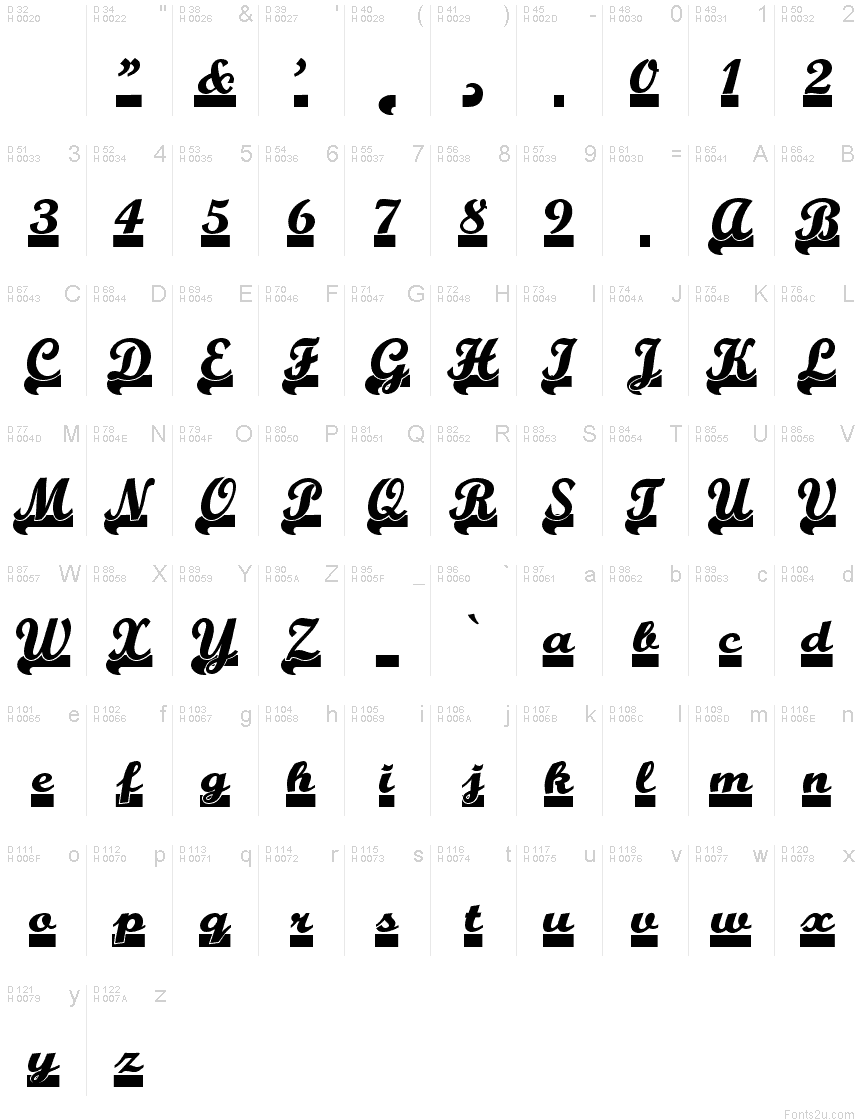
TeamSpirit
Team Spirit autorstwa Nicka Curtisa to darmowy, sportowy krój pisma typu script, utrzymany w duchu klasycznego, drużynowego liternictwa. Litery płynnie łączą się ze sobą, tworząc rytmiczną całość, a szerokie pociągnięcia pędzla i długie podkreślenia sprawiają, że napisy wyglądają jak gotowe projekty na koszulki, proporczyki czy klubowe szyldy.
Font świetnie sprawdza się w logotypach sportowych, grafikach szkolnych, odzieży w stylu retro, nagłówkach plakatów i tytułach, w których podkreślenie staje się elementem kompozycji. Jako darmowy font idealnie nadaje się również do okładek, brandingu w formie odznak czy krótkich nazw na opakowaniach, które potrzebują klimatu „varsity” bez surowości blokowych krojów.